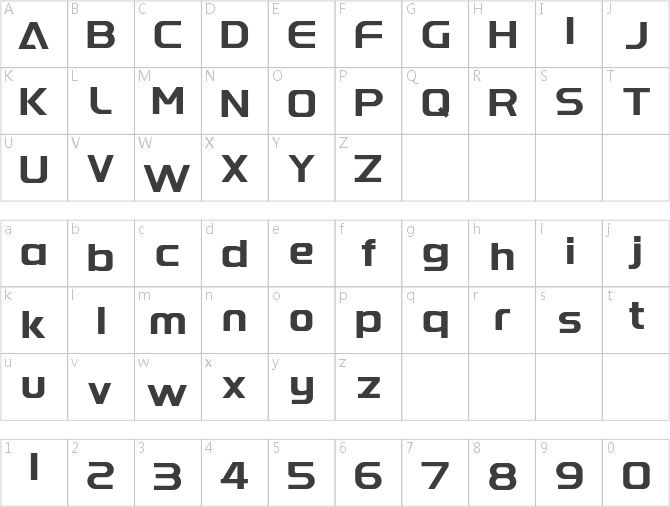
ZiTiQuanXinYiLOGOTi
ZiTiQuanXinYiLOGOTi字体下载字体圈欣意LOGO体
这是一套全英文字库,适用于标题、LOGO设计等场合使用,所以只做了52个英文10个数字和几个标点。
ZiTiQuanXinYiLOGOTi字体字体圈欣意LOGO体字库是一款让人赏心悦目、百看不厌的英文字体,适合各类广告和产品包装设计应用,字体大小0.01MB,格式为ttf字体,上传用户是小李哥/,作者/版权方为字体圈